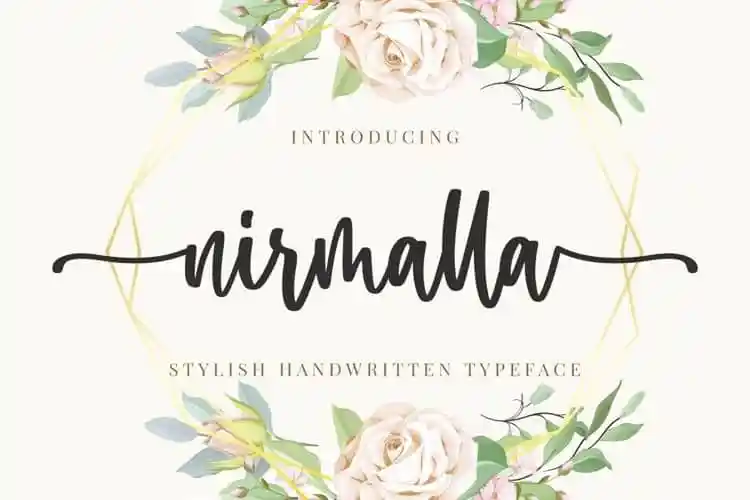
Nirmalla Calligraphy Font – Download Grátis
A Nirmalla Calligraphy Font é uma nova descoberta para amantes de tipografias modernas com um estilo alegre e original. Ela foi criada pela RStudio, apresentando uma mistura única de estilo de calligrafia artesanal, caracteres decorativos e linhas que dançam ao longo da linha base. Esta fonte PUA está disponível, permitindo que você facilite o acesso a todos os símbolos e swashes em seu design. Ela tem um baseline variável, linhas suaves, belos grafismos e alternativas estonteantes, mantendo fortemente sua influência chamigrafica enquanto parece contemporânea e nova. A Nirmalla Calligraphy é uma fonte perfeita para quem procura o charme do calligráfico em um estilo atual e moderno. Adquira-a hoje e elevie seus trabalhos!